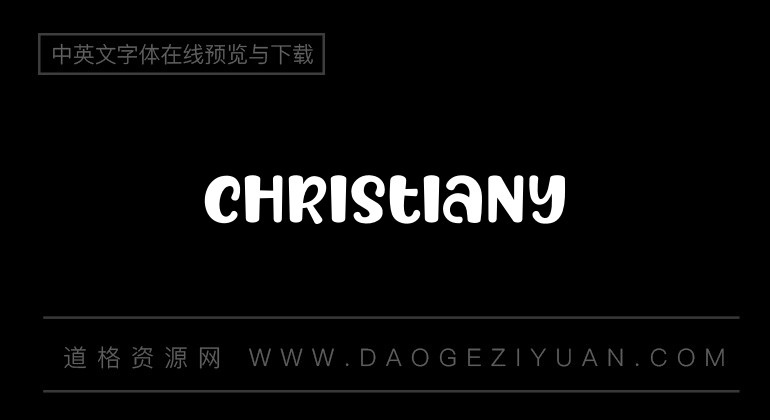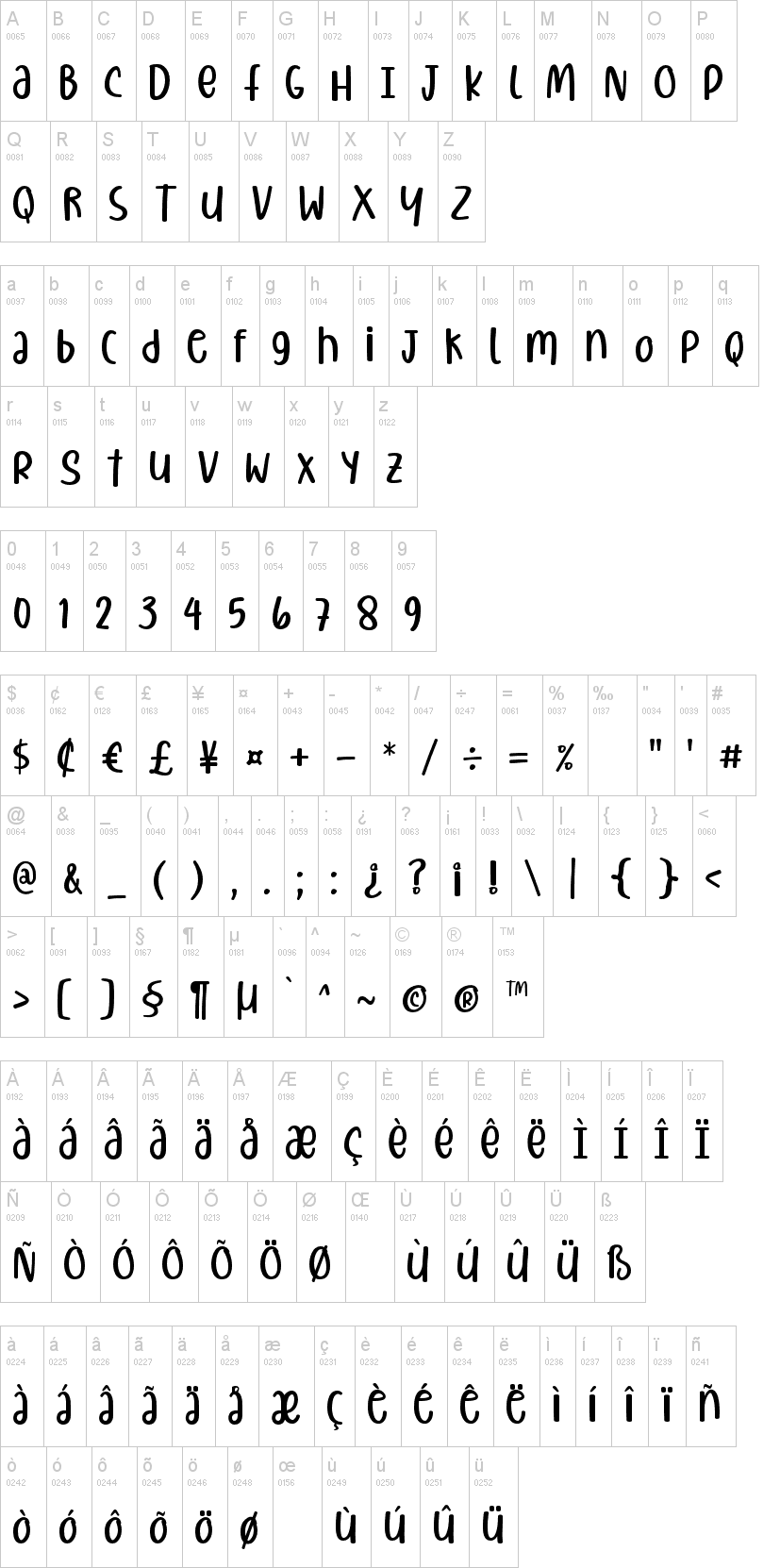
Christiany 字体是一种手写风格的字体,由著名设计师Christian Thalmann创作。它采用了现代设计元素,拥有清晰的表现形式,可以提供精致的文字效果。它有着优雅的外观,可以更好地表达文字的意义。Christiany字体可用于许多不同的设计项目,如广告、网页设计、报纸、杂志、海报、标志和书籍封面等。内容介绍
Christiany是一款非常不错的手写艺术字体,具有很好的视觉感,适合于文化类的宣传设计、商业类品牌的广告和产品包装设计以及个性化文字排版等较多场景。